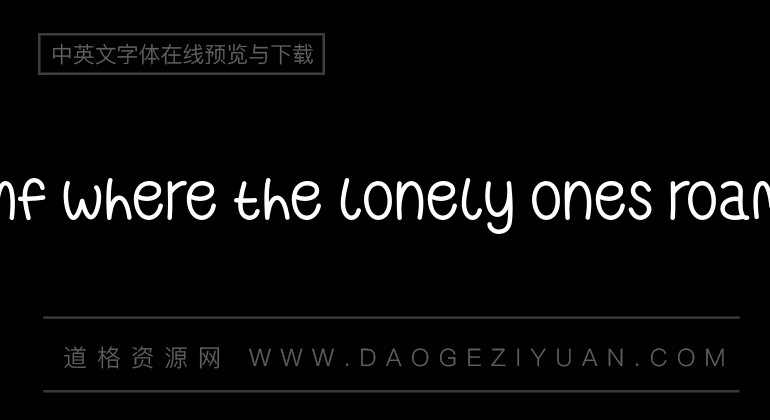
"Mf Where The Lonely Ones Roam" 是一种手写风格的字体,具有独特的个性和魅力。它的字母形状流畅、自然,非常适合用于卡片、海报、标语、书籍封面等场合,具有很高的可读性。 "Where The Lonely Ones Roam" 字体大小和颜色可以根据需要进行调整,因为它支持多种格式,包括 TTF 和 OTF。这种字体的设计灵感可能源自于手写信件或日记,因此它的笔画有些紧凑,但仍然非常清晰。 总的来说,“Mf Where The Lonely Ones Roam” 是一种非常有趣和个性化的字体,适用于多种场合。内容介绍
Mf Where The Lonely Ones Roam是一款非常不错的手写艺术字体,具有很好的视觉感,适合于文化类的宣传设计、商业类品牌的广告和产品包装设计以及个性化文字排版等较多场景。